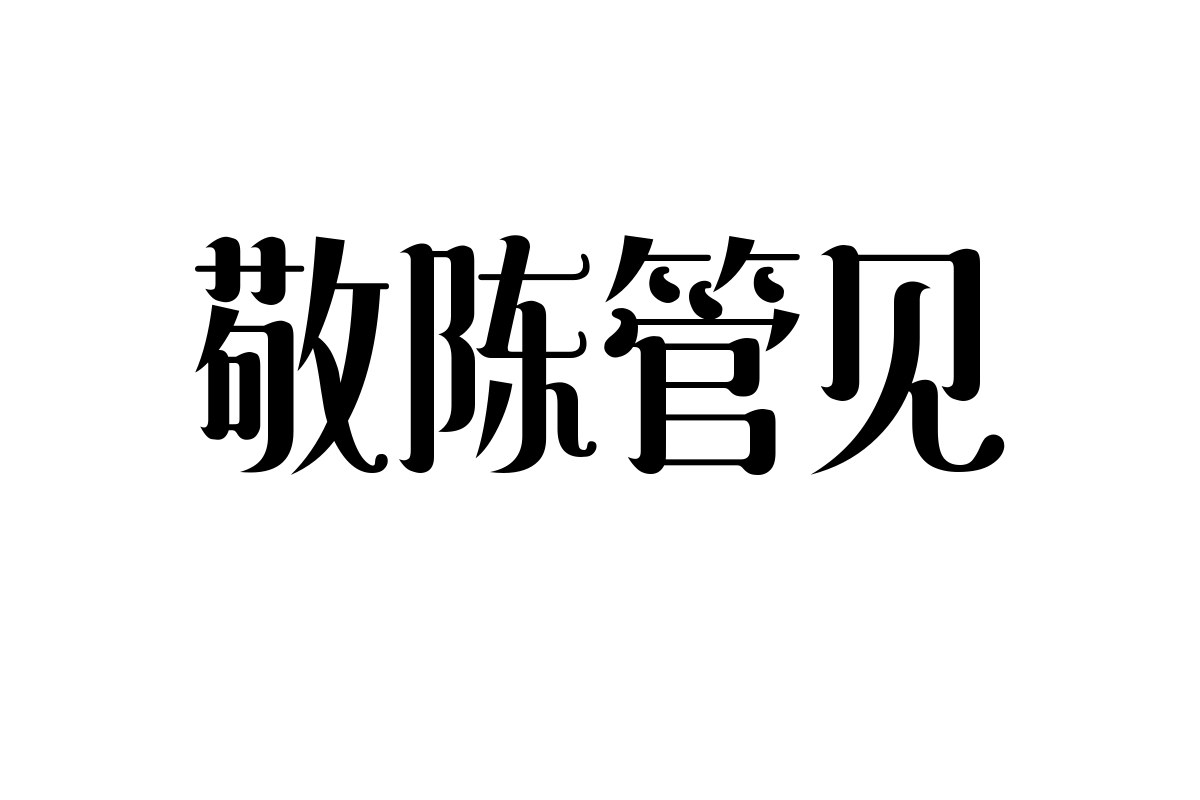
妙妙体是一种独特的字体设计风格,其特点是字形结构紧凑、线条流畅、富有动感。这种字体的设计灵感来源于自然界中的动植物,通过巧妙的笔画组合和形态变化,展现出一种生动活泼的艺术效果。
妙妙体的笔画简洁明了,每个字都由基本的笔画构成,但通过巧妙的排列组合,形成了独特的视觉效果。例如,“木”字的笔画简单,但通过巧妙地弯曲和连接,形成了一种生机勃勃的感觉;“水”字则通过流动的线条和弯曲的形态,给人一种流动的感觉。
妙妙体的字体风格多样,既有传统的楷书、行书等,也有现代的创意字体。无论是用于标题、正文还是装饰性文字,都能展现出不同的艺术魅力。同时,妙妙体也适合用于各种场合,如广告设计、海报制作、网页设计等,能够为作品增添一份独特的艺术气息。
造字工房妙妙体